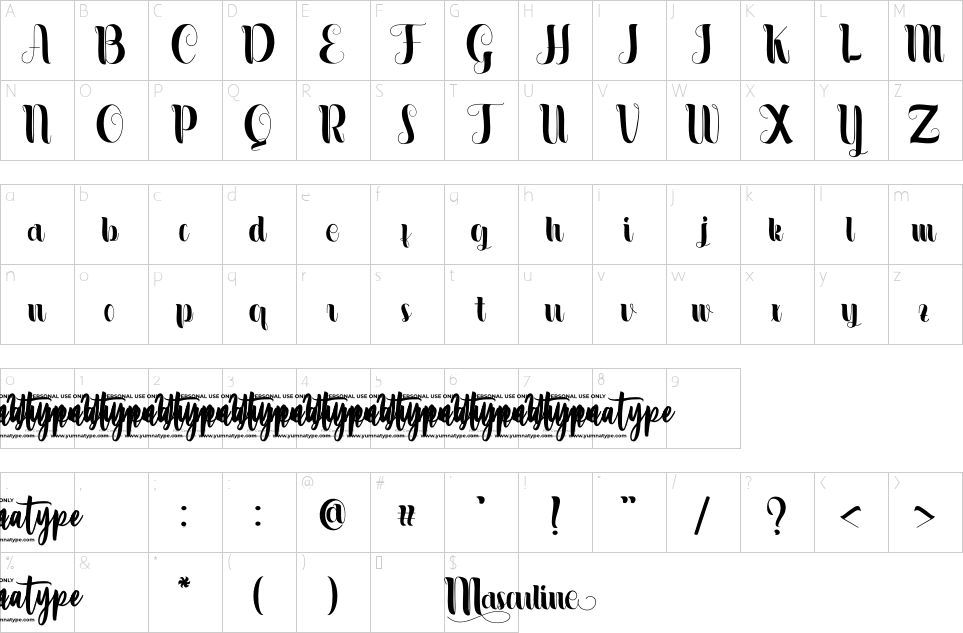
A fonte Masculine é uma escolha perfeita para quem busca uma aparência robusta e moderna. Criada pelo designer Yumna type, esta fonte foi projetada para ser usada tanto no Windows quanto no Mac. Seu estilo masculino e robusto se destaca como uma ótima opção para nomes de negócios, logotipos e design gráfico. Com sua facilidade de uso e alta qualidade, é um recurso indispensável para qualquer designer ou profissional de design. Descarregada 3.024 vezes, a Masculine font tornou-se uma opção popular para aqueles que buscam uma fonte poderosa sem grandes custos. Que tal adicionar um toque de masculinidade e robustez a seus projetos com esta fonte?